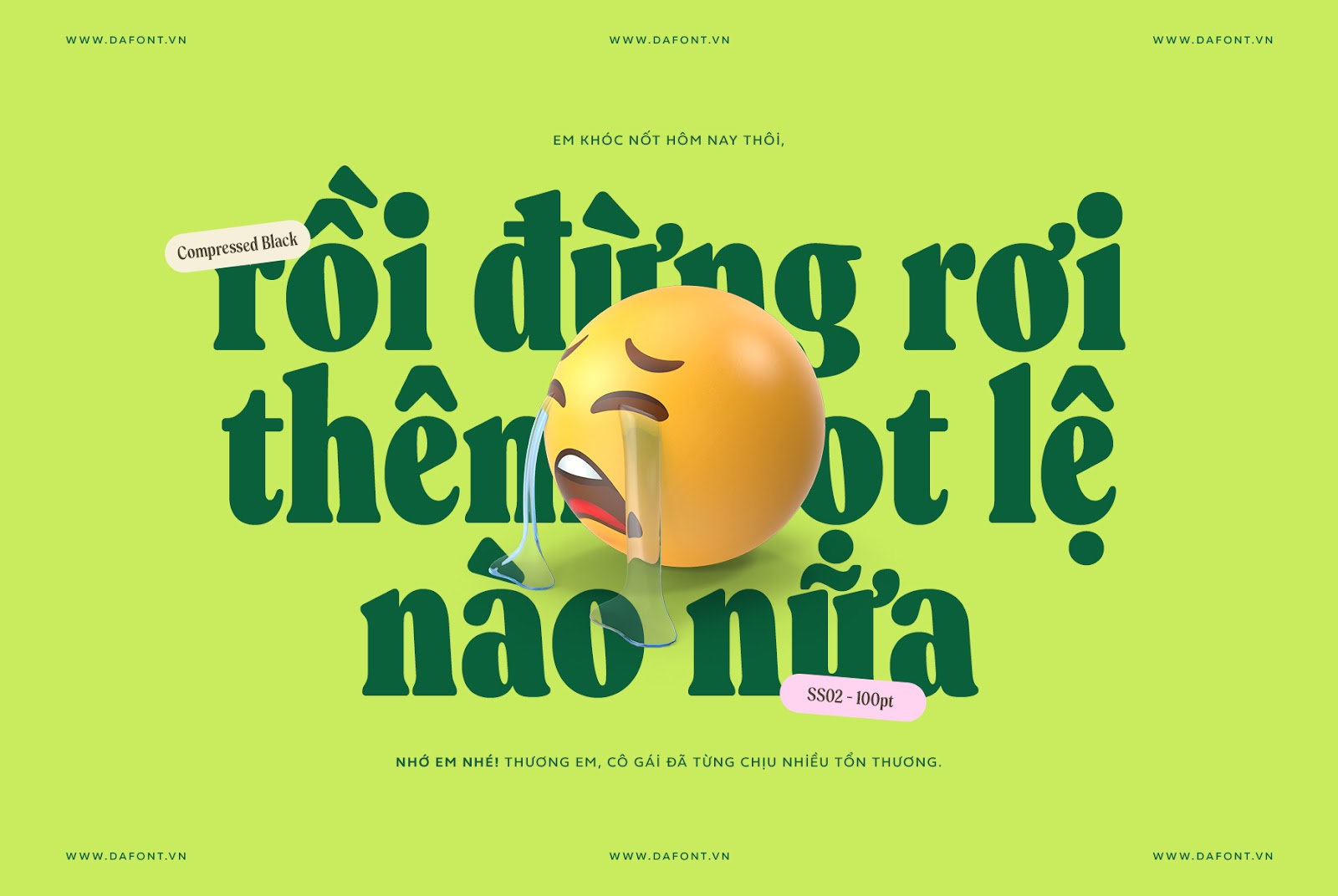
Trọn bộ font Ltt Recoleta Việt hóa (24 font)
LTT Recoleta lấy cảm hứng từ các font nổi tiếng của thập niên 70 như Cooper và Windsor, đồng thời pha trộn nét mềm mại, bo tròn đặc trưng của Cooper với những đường xiên uyển chuyển của Windsor, tạo nên một kiểu chữ vừa thân thiện, vừa sang trọng.
Những đặc điểm nổi bật giúp LTT Recoleta:
- Đường cong mềm mại, cạnh bo tròn: Tạo cảm giác thân thiện, gần gũi nhưng vẫn tinh tế, phù hợp với xu hướng thiết kế hiện đại đề cao sự ấm áp và cá tính riêng.
- Tương phản nét đậm – mảnh cao: Giúp font nổi bật và thu hút sự chú ý, rất thích hợp cho tiêu đề, logo và các điểm nhấn trong thiết kế hiện đại.
- Hình dáng chữ độc đáo: Các ký tự cách điệu như chữ “a” thường và chữ “R” hoa tạo dấu ấn riêng mà không làm giảm khả năng đọc, giúp thiết kế vừa có nét cá tính vừa dễ tiếp cận.
- Đa dạng trọng lượng và chiều rộng: Với 24 style từ Thin đến Black và ba độ rộng (Normal, Condensed, Compressed), LTT Recoleta mang lại sự linh hoạt tối đa để ứng dụng trong nhiều loại thiết kế hiện đại khác nhau, từ web đến in ấn.
- Khả năng kết hợp tốt với các font sans-serif: Giúp tạo sự cân bằng giữa cổ điển và hiện đại, phù hợp với xu hướng thiết kế đa dạng ngày nay.
Những đặc điểm này giúp bộ font LTT Recoleta Việt hóa vừa giữ được nét hoài cổ tinh tế, vừa đáp ứng được yêu cầu về tính thẩm mỹ và chức năng trong thiết kế hiện đại.
Bộ font được Việt hóa rất kỹ, tất cả các ký tự và dấu tiếng Việt đều được tối ưu hóa lại, kerning đầy đủ, 1 số ký tự thay thế cũng được Việt hóa và dễ dàng sử dụng bằng tính năng Opentype.